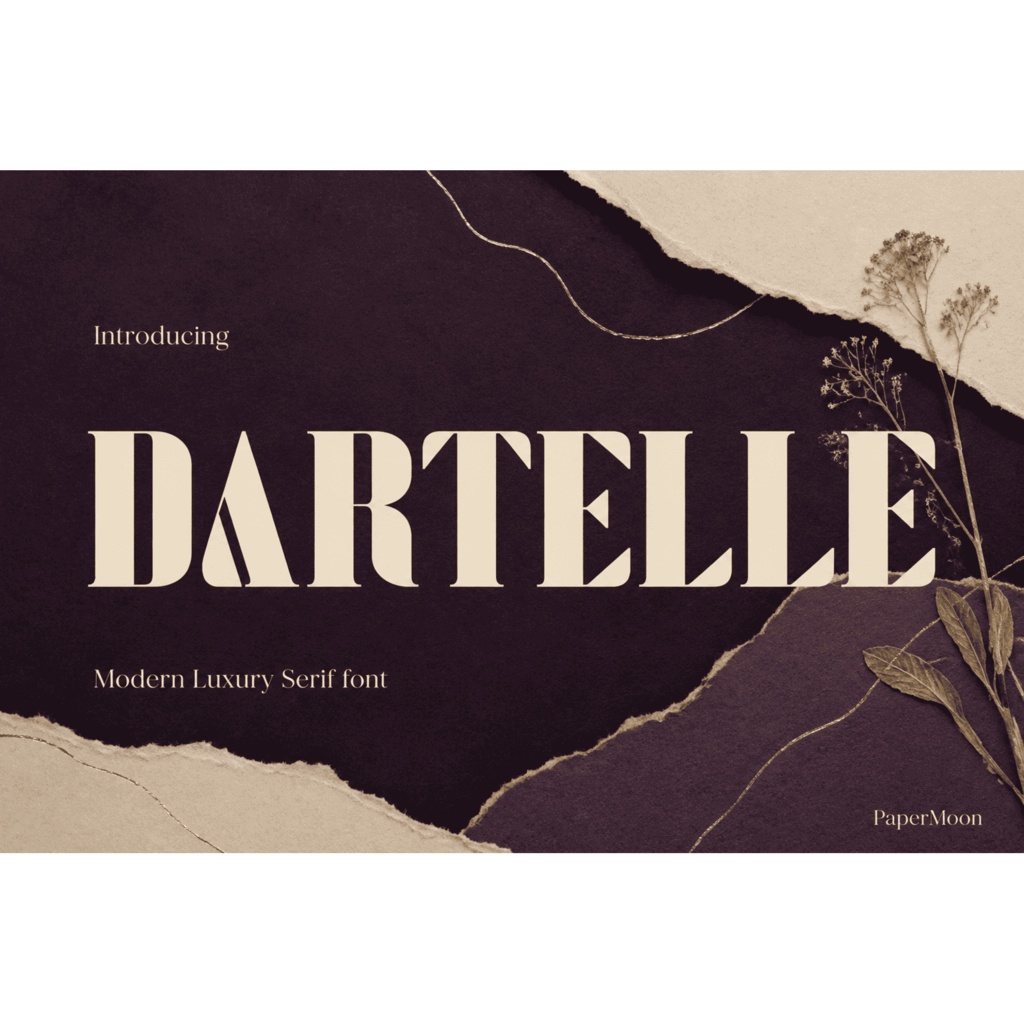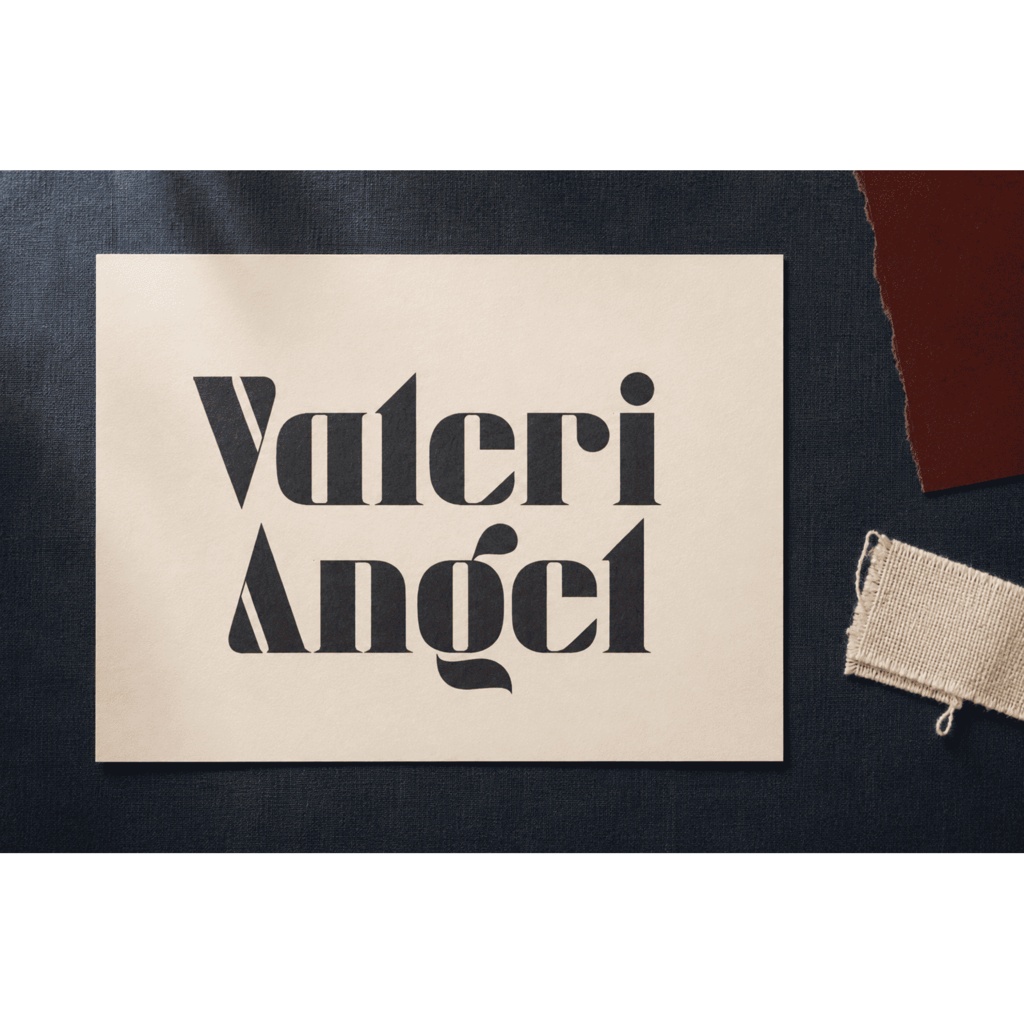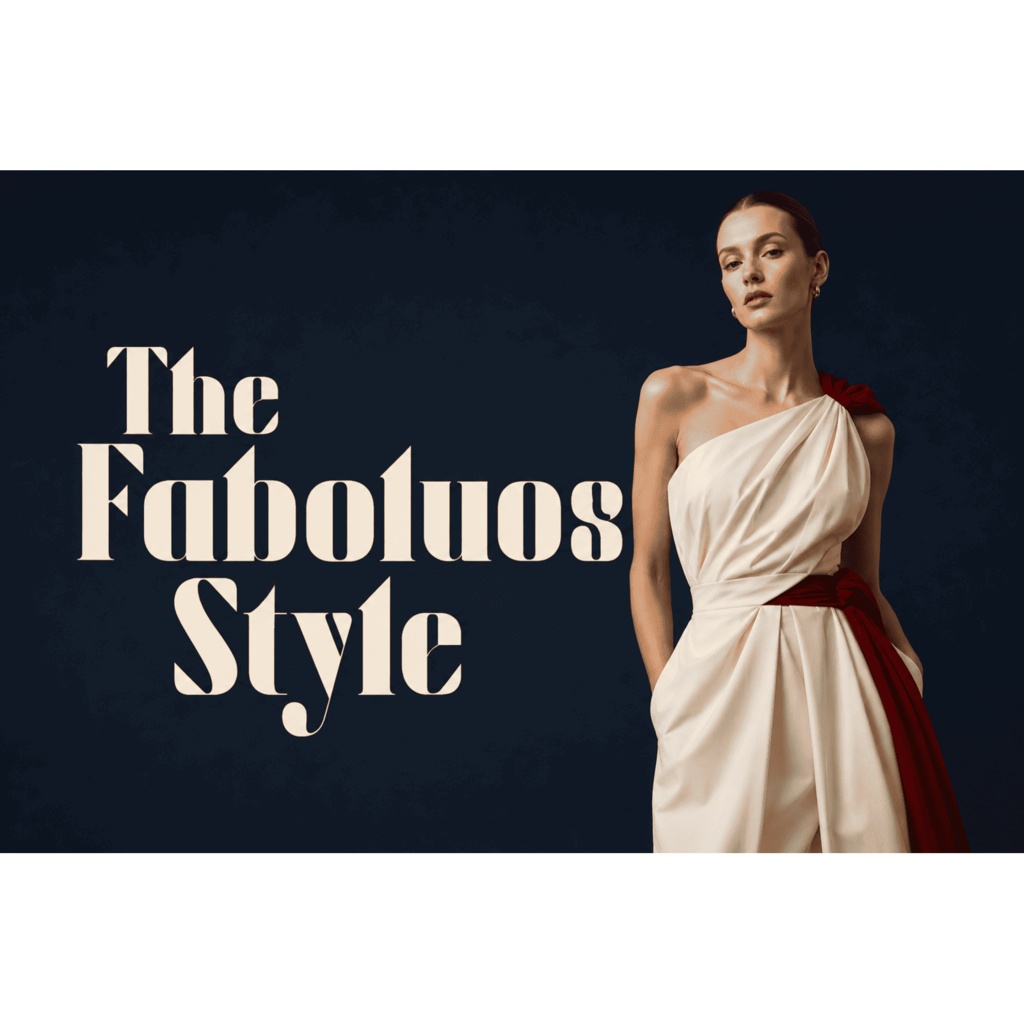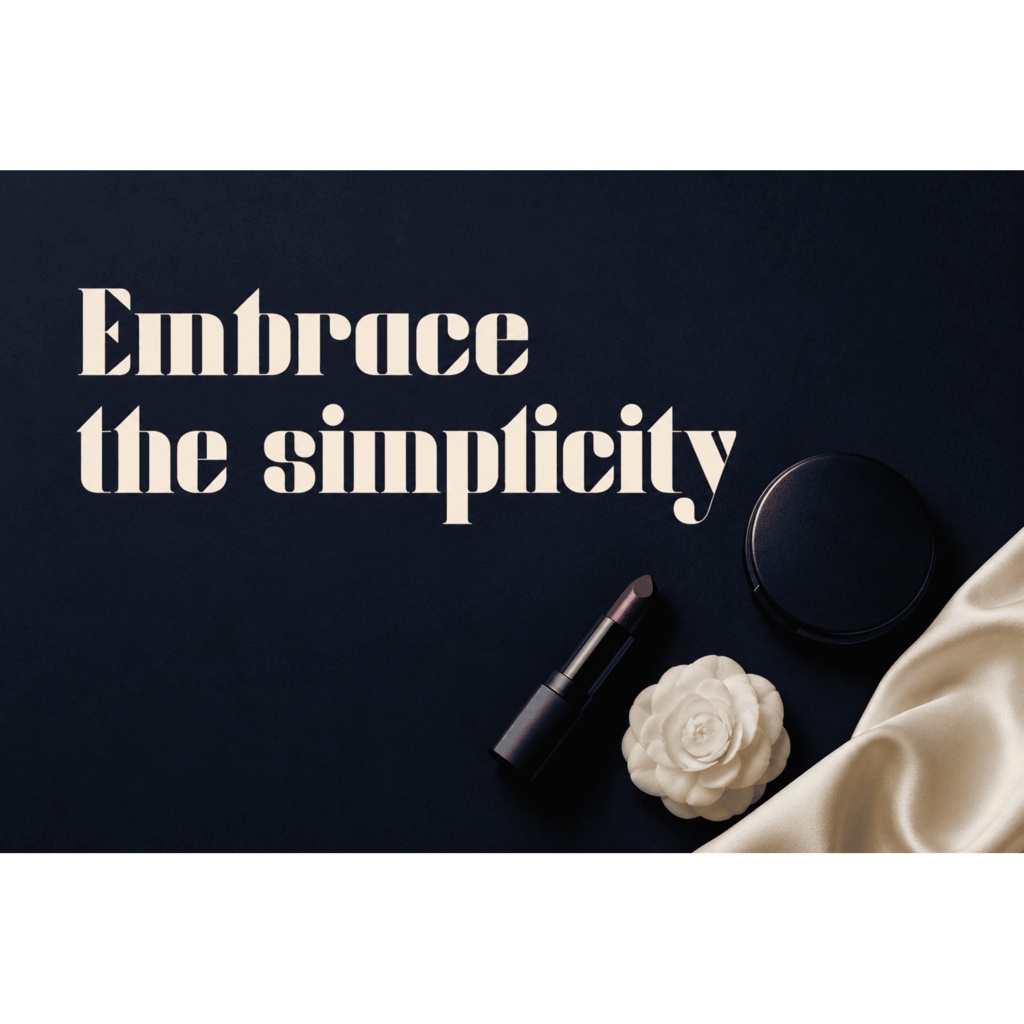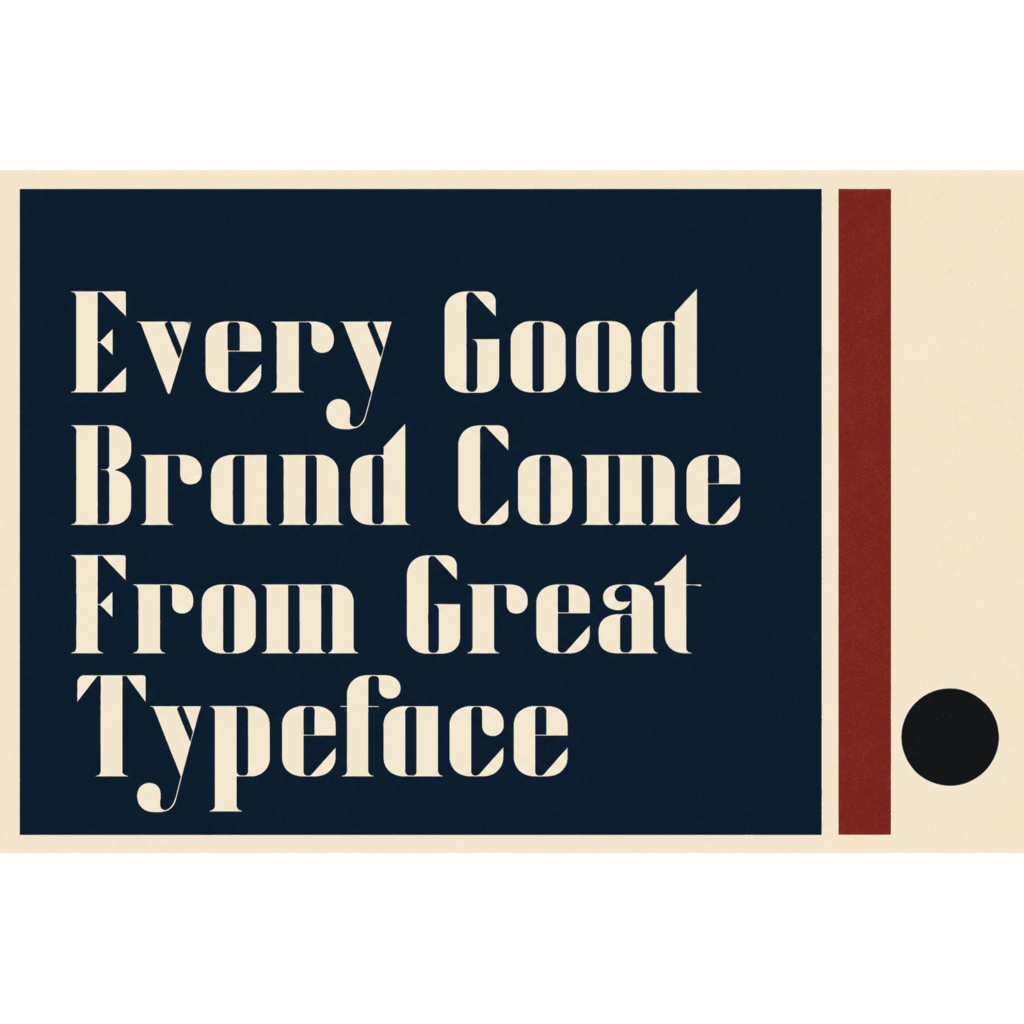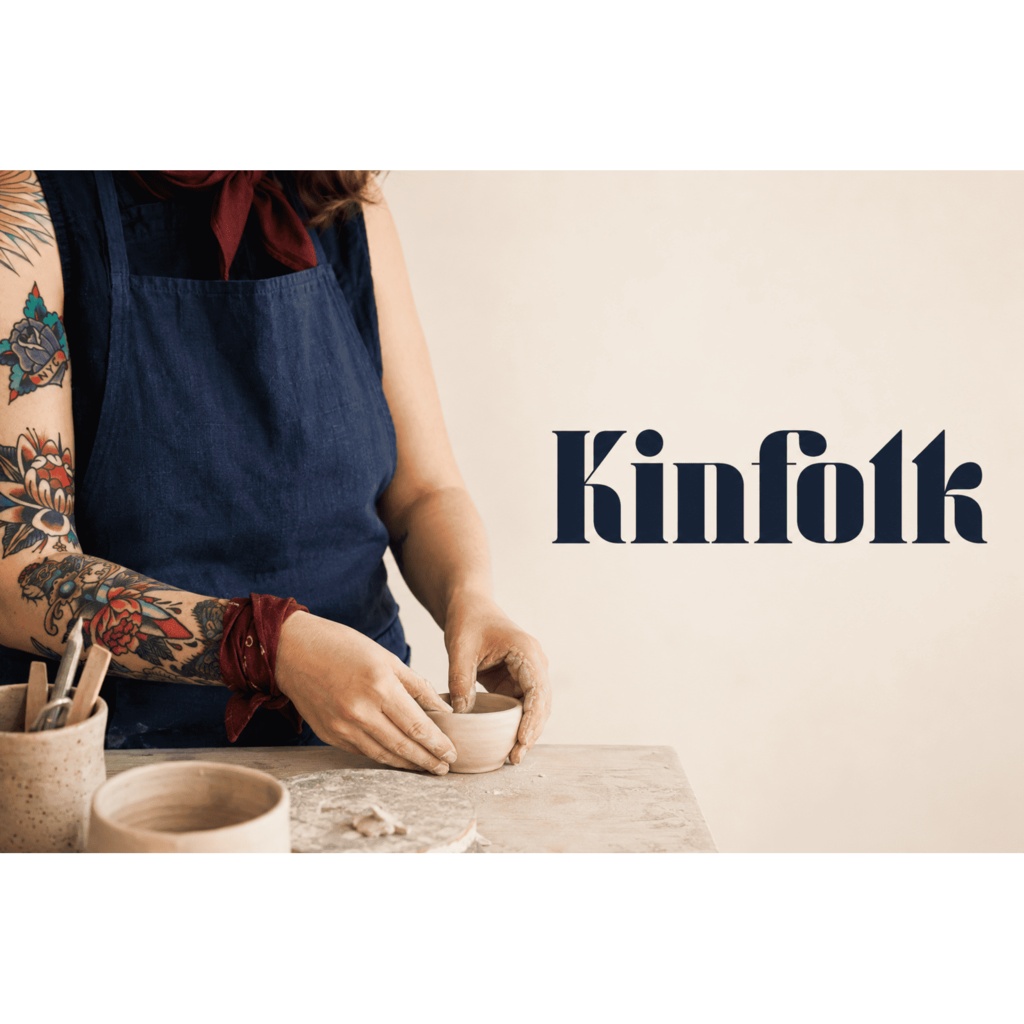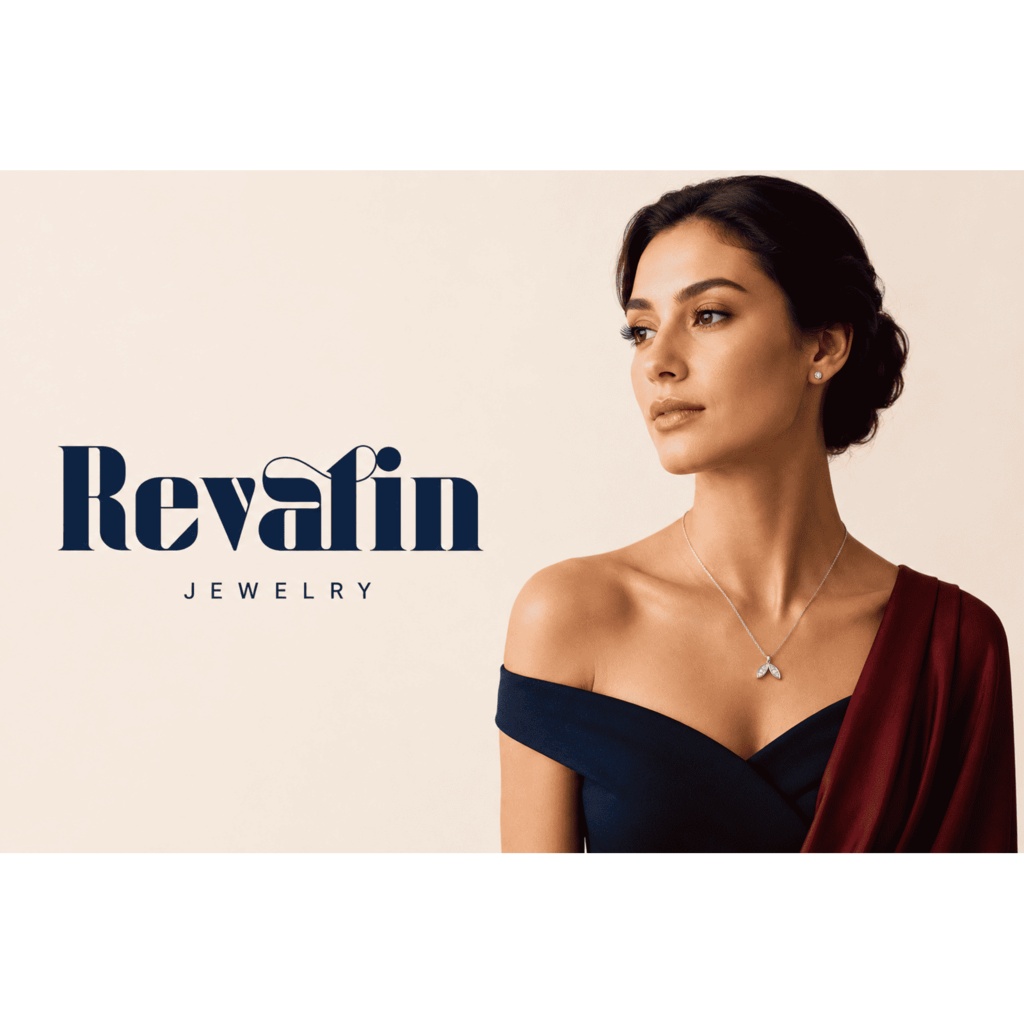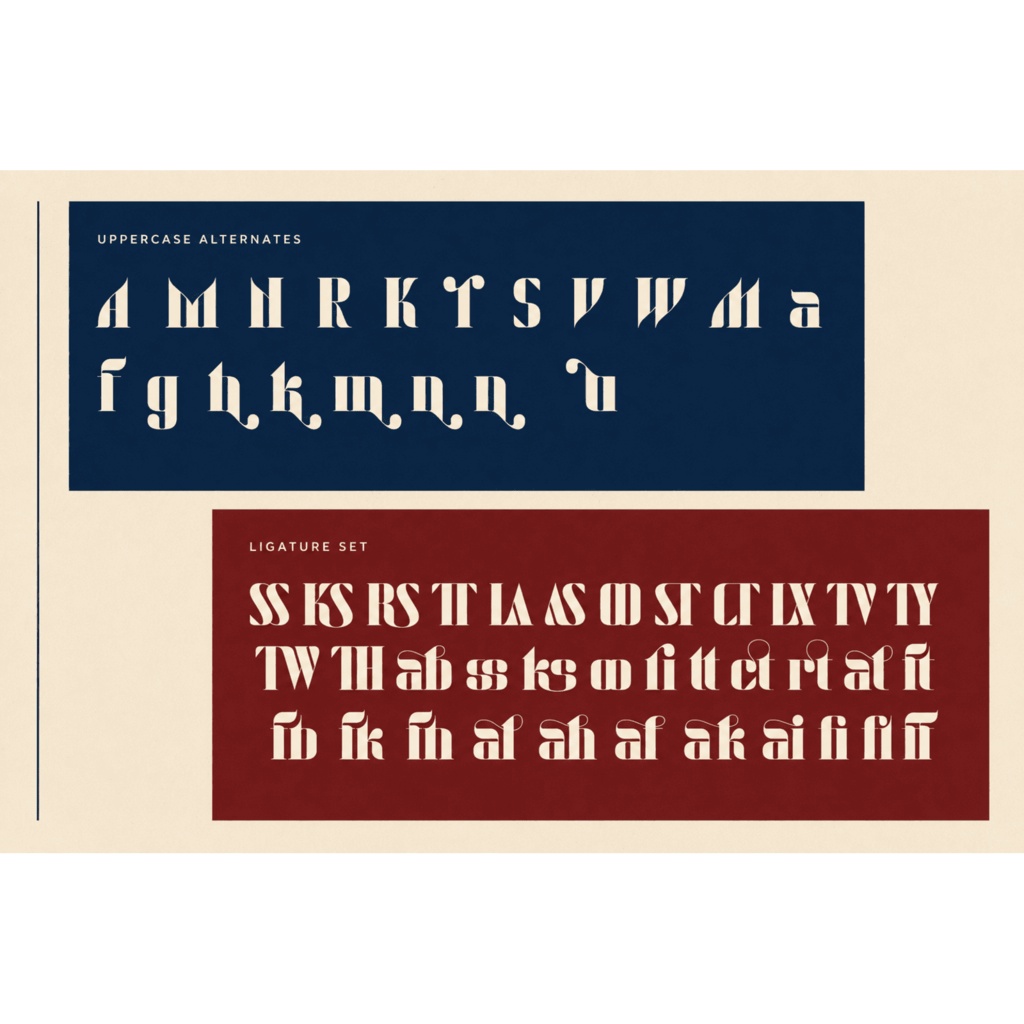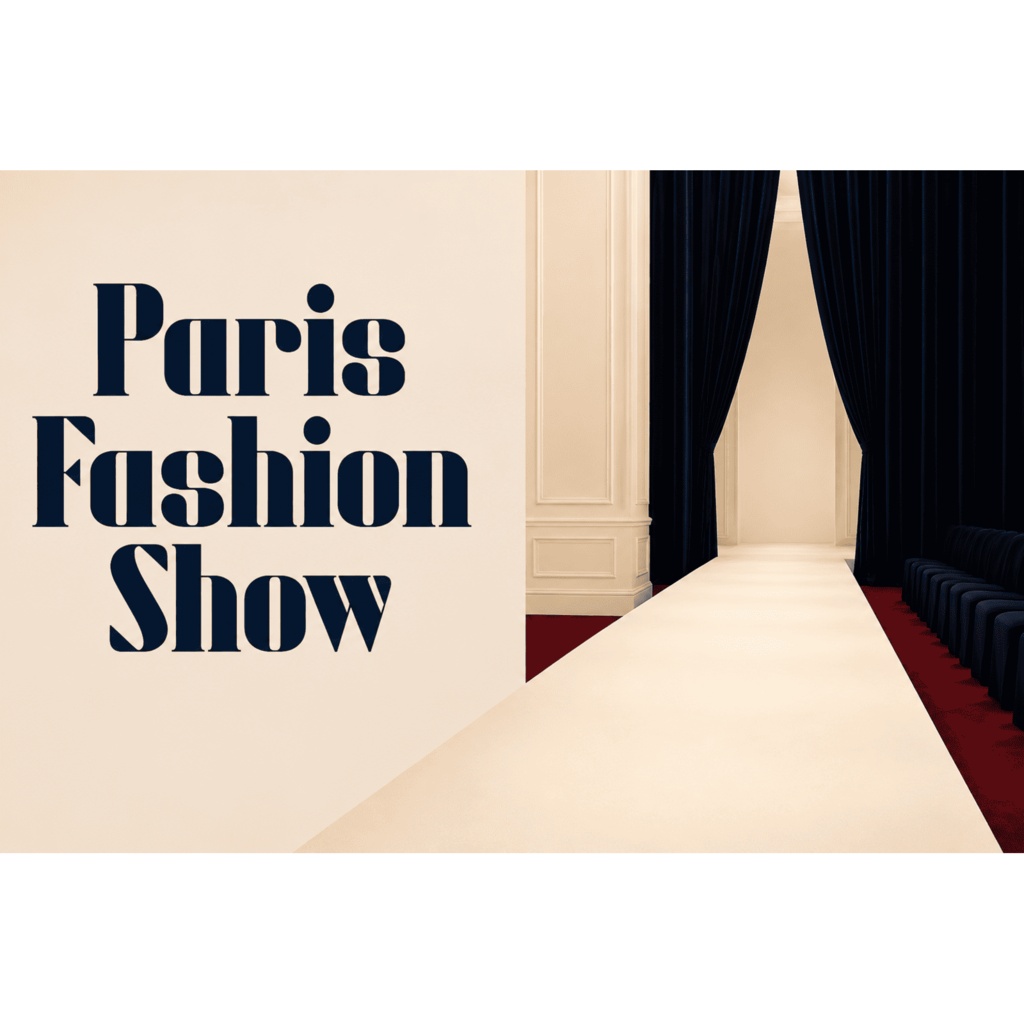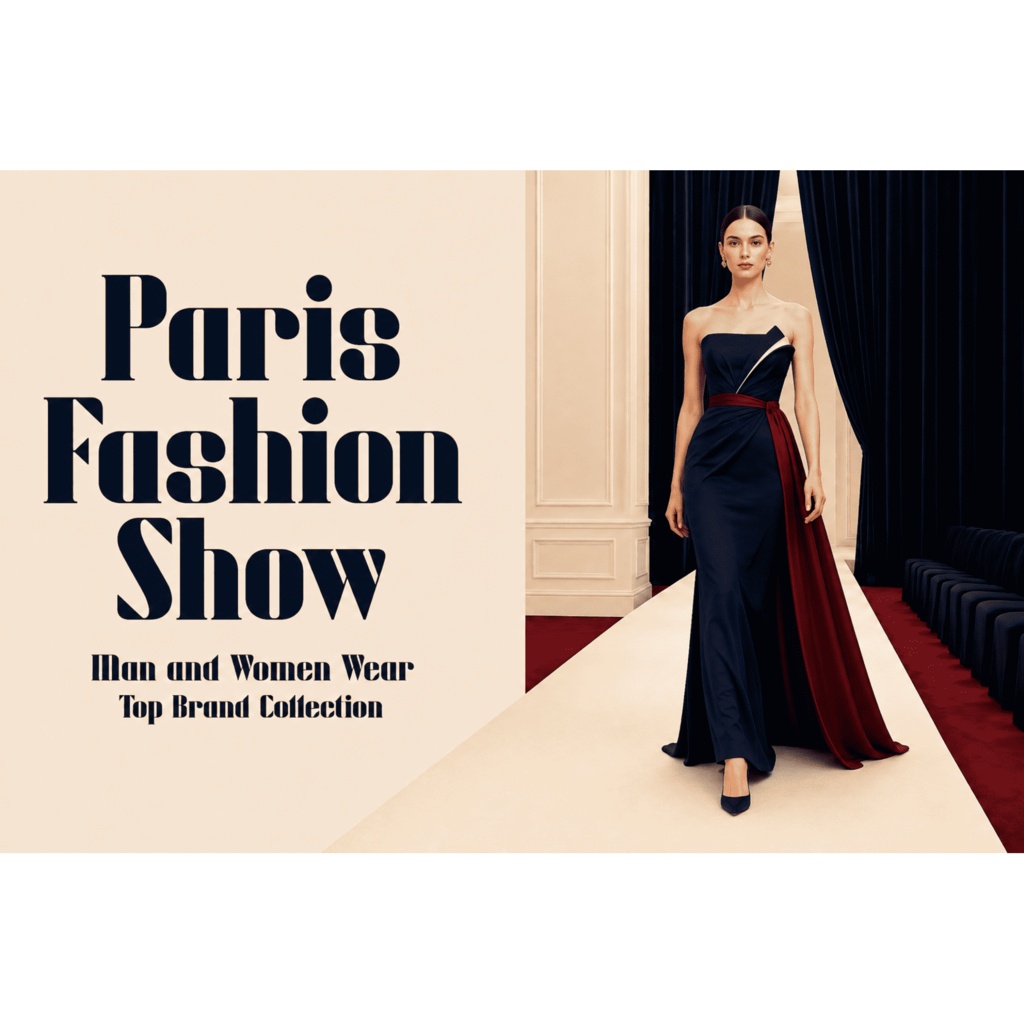
Dartelle | エレガントな欧文セリフフォント | ロゴ・ブランディング・ウェディング
Dartelle(ダルテール)は、エレガントでモダンな欧文セリフフォントのデュオです。落ち着いた Regular と流麗な Italic の2スタイルを収録し、ファッション・ビューティーブランドのロゴ、ブティックのブランディング、ウェディング招待状、エディトリアル・雑誌の見出し、パッケージやラベルなど、上品な仕上がりが求められるシーンに最適です。 短い見出しやロゴタイプではコントラストのある字形が映え、Regular はブランド名や安定した土台に、Italic は招待状のディテールやキャプションに流れを与えます。Bold・Bold Italic は含まず、2スタイルを意図的に組み合わせて使うデュオ構成です。なお、本フォントは日本語フォントではありません(ラテン文字専用)。 収録内容 - Dartelle Regular(正体)と Dartelle Italic(斜体)の2スタイル、計8ファイル - 各ソースマスター 291 グリフ - OpenType 機能: オルタネート(aalt / salt / ss01 / ss02)、合字(liga / dlig)、分数(frac)、序数(ordn)、上付き文字(sups)、調整済みカーニング(GPOS kern) 対応文字 - ラテン文字のみ: A–Z / a–z、数字、約物、記号(基本ラテン文字、ラテン1補助、および選定されたラテン拡張A/B) - 西ヨーロッパ・中欧のラテン文字テキストに対応(英語・フランス語・スペイン語・ドイツ語・イタリア語・ポルトガル語・オランダ語・スウェーデン語ほか) - 日本語(ひらがな・カタカナ・漢字)、キリル文字、ギリシャ文字は含まれません。ご購入前に必要な文字の有無をご確認ください。 用途 - ファッション・ビューティーブランドのロゴ・ワードマーク - ブティックやプレミアムブランドのブランディング - ウェディング招待状・結婚式のペーパーアイテム - エディトリアル・雑誌の見出し - 商品パッケージ・ラベル・写真のウォーターマーク - 広告・SNS グラフィック・ポスター・Web 見出し 形式 - Dartelle-Regular.otf / .ttf / .woff2 - Dartelle-Italic.otf / .ttf / .woff2 - デスクトップ・印刷用途は OTF / TTF、Web 用途は WOFF / WOFF2 を @font-face で利用します。 対応環境 - Windows / macOS - Adobe Photoshop / Illustrator / InDesign、Affinity、Figma、Canva、Procreate、Microsoft Word、Cricut Design Space、Silhouette Studio、その他 OTF / TTF を読み込めるアプリケーション - インストール後はアプリケーションの再起動が必要です。オルタネート・合字など高度な OpenType 機能は各ソフトの Glyphs / OpenType パネルからアクセスします。対応状況はソフトウェアにより異なります。 利用許諾 - 本コピー作成時点ではライセンス条項は未確定(UNKNOWN)のため記載しません。出品前にライセンスファイルをご確認のうえ、商用利用の可否、再配布・再販、埋め込み、テンプレート利用などの正確な条項をご記載ください。 - ライセンス状況: 未確認(UNKNOWN)。出品時に出品者側での確認待ちです。 更新 - フォント名: Dartelle(確定名)。フォントデュオ(Regular + Italic の2スタイル。Bold / Bold Italic なし) - グリフ数: 各ソースマスター 291 グリフ - OpenType: aalt / salt / ss01 / ss02 / liga / dlig / frac / ordn / sups、GPOS カーニング - 形式: OTF / TTF / WOFF / WOFF2(計8ファイル) - 文字セット: ラテン文字のみ(基本ラテン文字、ラテン1補助、選定ラテン拡張A/B)。日本語・キリル・ギリシャは非対応 - 既存リストの記載によれば Copyright (c) 2026 PaperMoon(出品時にご確認ください)